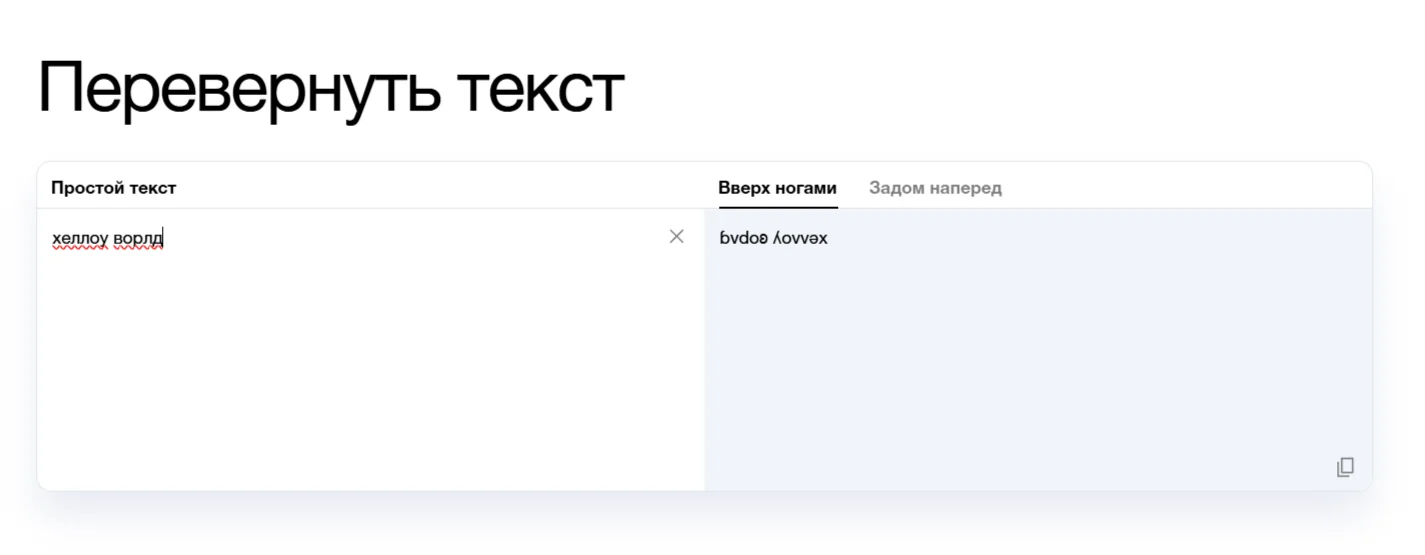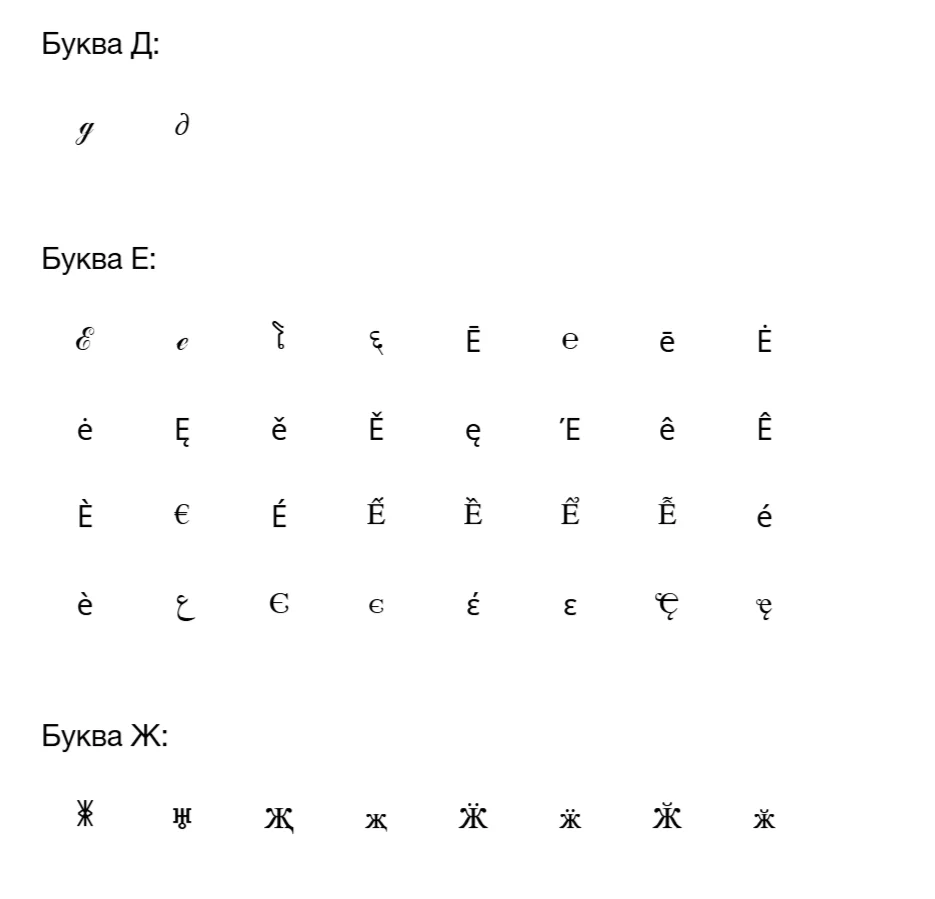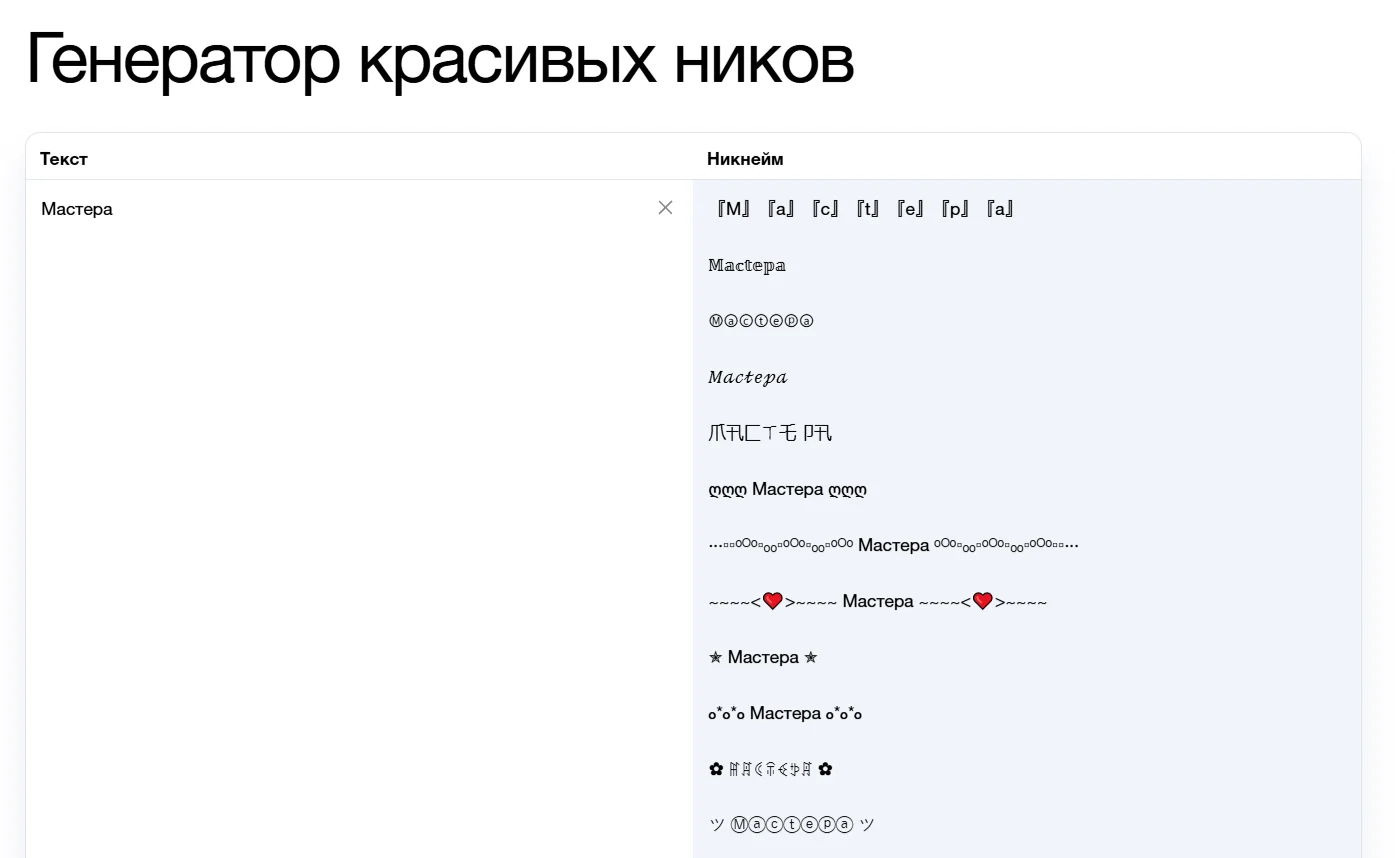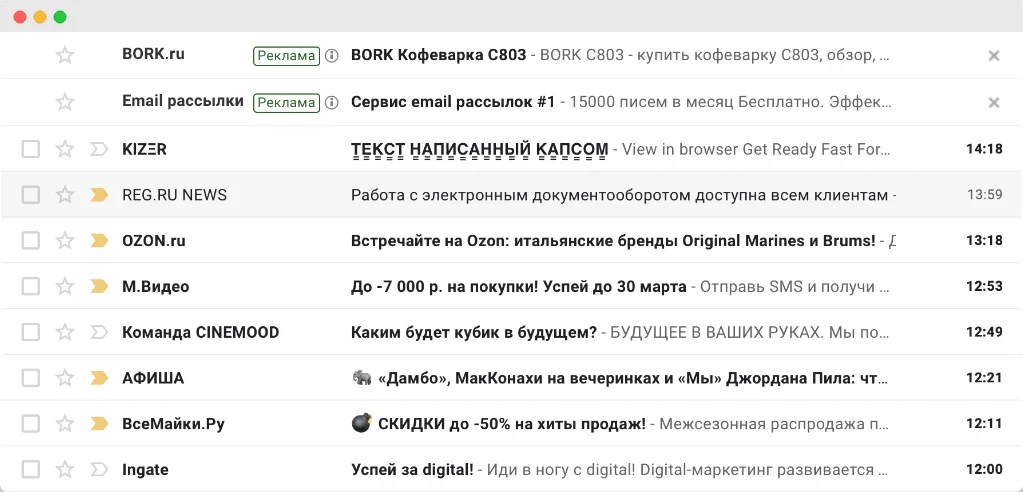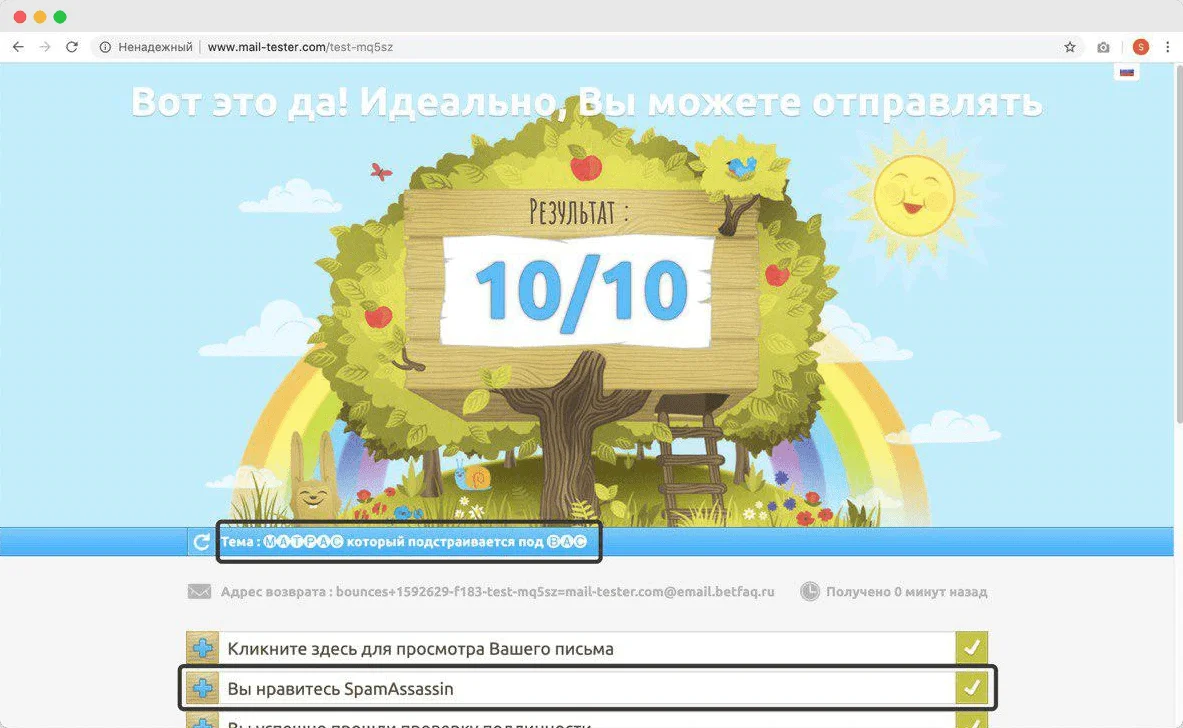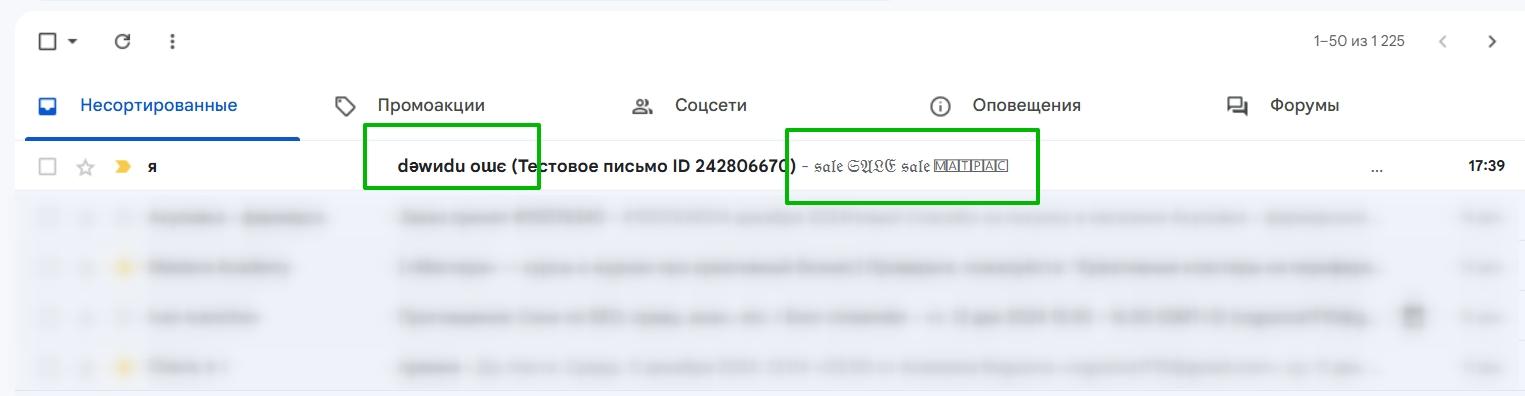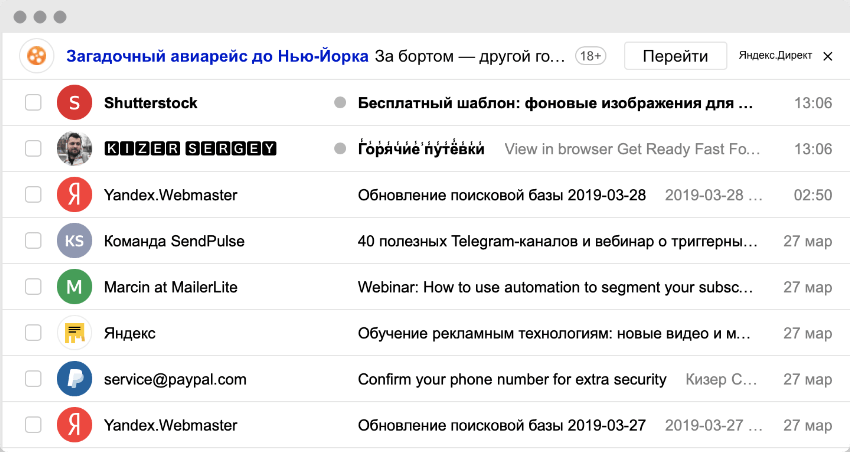
Возвращаем в моду готический шрифт и странные буквы
Компании очень стараются, чтобы выделится в почтовых ящиках: они используют эмоджи и креативные заголовки, экспериментируют с прехедерами. Но эти приёмы популярны среди маркетологов и уже вряд ли удивят подписчиков.
А как насчёт того, чтобы проигнорировать стили темы и использовать в ней декоративные шрифты? Это привлекает внимание:
Чтобы поставить новый шрифт в теме или графе «Отправитель», не нужно использовать CSS-стили или атрибуты HTML — более того, для этих полей это просто невозможно. Поменять шрифт можно только с помощью Юникода.
Юникод — стандарт кодирования символов. Когда мы используем эту кодировку, текст превращается в набор символов с определёнными характеристиками. Примеров использования Юникода много: например, эмоджи — часть этой кодировки.
Увы, но вариантов для креатива на кириллице, как волос на голове лысого из «Браззерс» — катастрофически мало. У большинства кириллических знаков просто нет аналогов в Юникоде.
Зато кириллицу, например, можно перевернуть.
С латиницей дела обстоят лучше. Как это можно использовать:
Также с латинскими буквами можно поразвлечься при помощи дополнительных стилизаций Юникода, например, инвертировать в готический шрифт (учтите, что периодически он нечитаем, особенно если писать капсом).
Как вы понимаете, несмотря на ограничения, выкрутиться можно.
Проще всего конвертировать через сервис Symbl от, собственно, Юникода. Здесь есть не только таблица символов, из которой можно собрать нужное слово или текст вручную, но и множество дополнительных инструментов, которые работают тут же — достаточно просто ввести слово.
Всё, что остаётся вам, как создателю рассылки — скопировать текст из правой части редактора и вставить в тему, прехедер или поле «Отправитель».
Также там есть целый раздел с «красивыми буквами» — вариантов достаточно и для латиницы, и для кириллицы. В последнем, правда, будет сложнее поддерживать единый стиль написания всех букв в слове, так как часть из них существуют только в латинице.
Если лень собирать слово вручную, можно обратиться к тому, что у Symbl называется «Генератор ников»: там достаточно ввести слово, и сервис предложит различные варианты написания — останется только протестировать, чтобы выбранный вариант точно сработал в почтовиках. С кириллицей тоже работает! Но сразу предупредим, что некоторые варианты выглядят, как будто вы вернули себе свой 2007-й.
Приём работает в таких почтовых приложениях:
Я проверил письмо с Юникодом в сервисе Mail-tester. Декоративные шрифты никак не влияют не репутацию email: